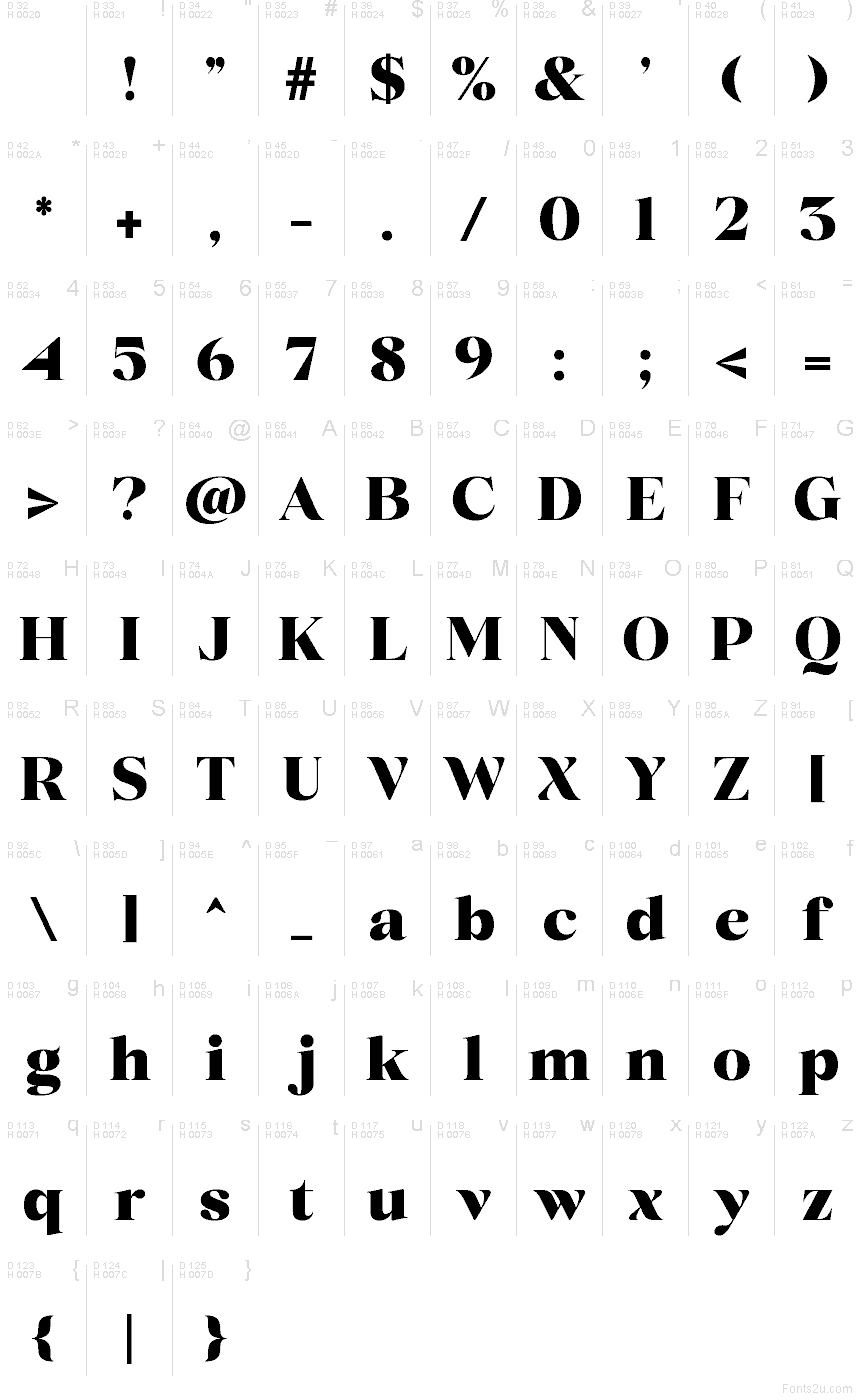
Scaver Black von Glyphminds Studios ist eine kostenlose, kontrastreiche Serifenschrift mit einer ausgeprägten modischen Editorial-Ästhetik. Die Buchstaben verbinden schwere, samtige Kurven mit scharf zulaufenden Spitzen, was dem Design eine dramatische, fast schon dekadente Wirkung verleiht, die weit über den klassischen Stil hinausgeht.
Es eignet sich perfekt für das Branding von Beauty- und Schmuckmarken, Magazin-Headlines, Album-Covern, Cocktail-Menüs und Titelkarten – überall dort, wo eine kostenlose Schrift mit einer reicheren, stilisierteren Stimme gefragt ist. Verwenden Sie sie für kurze Überschriften, Logos oder monogrammartige Initialen: Die schwungvollen Kurven und spitz zulaufenden Verbindungen verleihen selbst wenigen Buchstaben eine souveräne, skulpturale Präsenz.